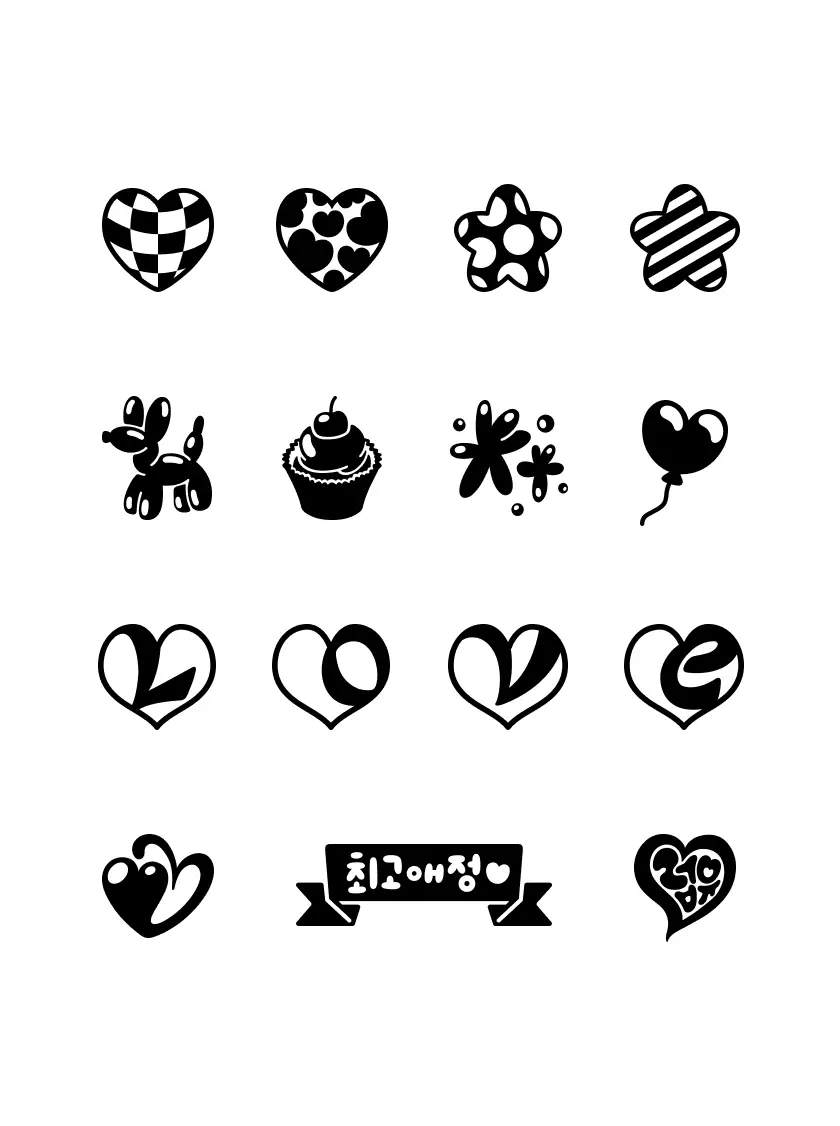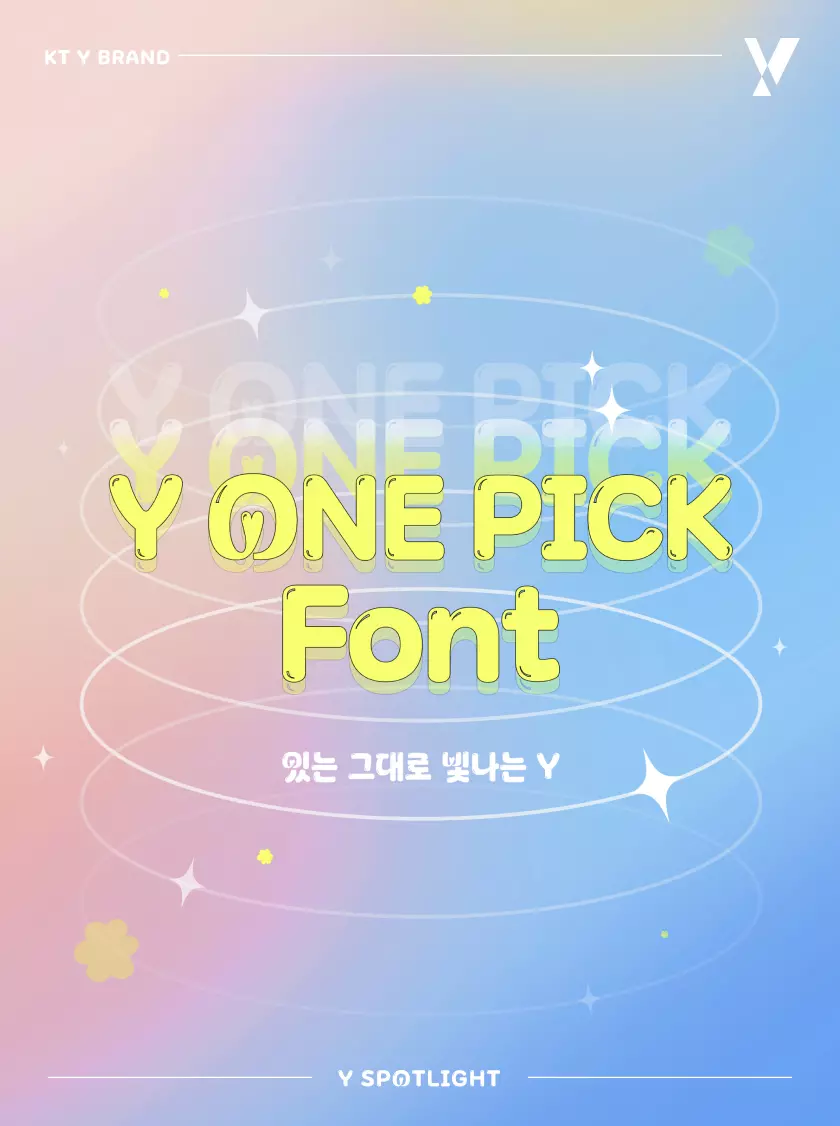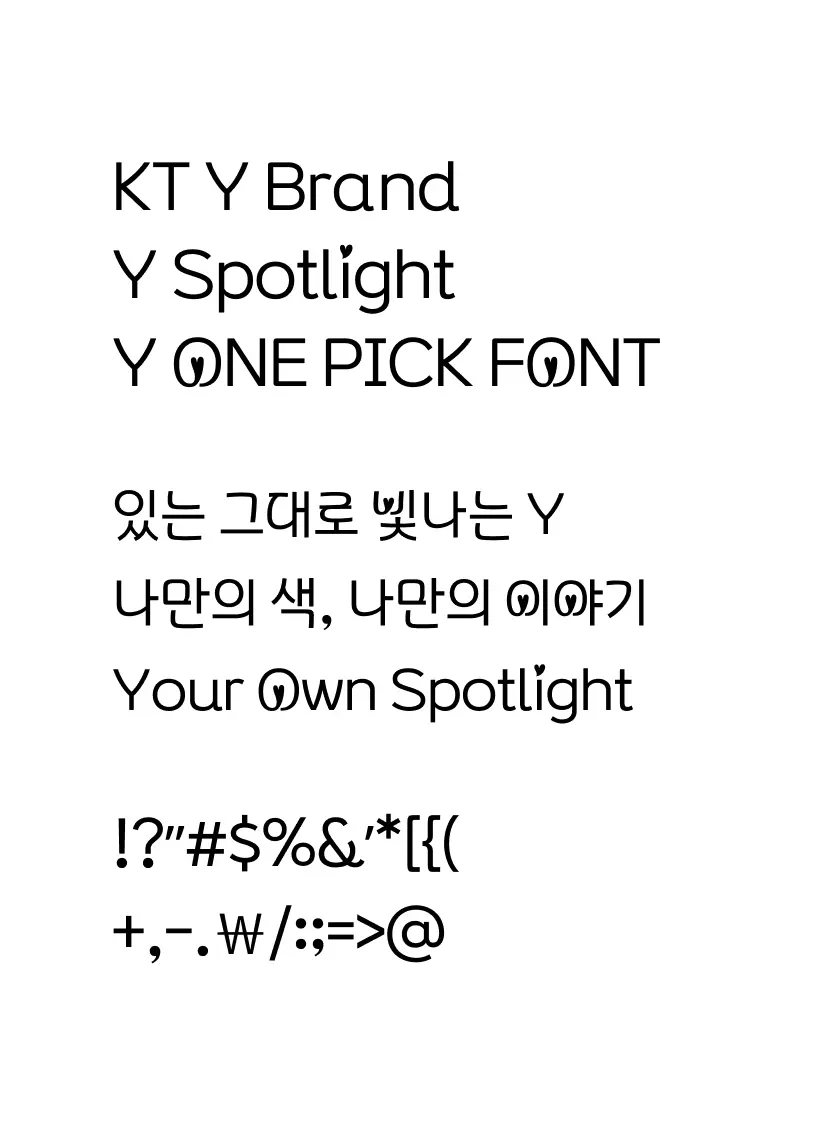
2024년 한글날을 맞이하여 무료 폰트로 배포한 KT Y최애체를 무료로 다운로드하는 방법을 살펴본다. 더불어 누구나 무료로 사용이 가능한 Y최애체를 컴퓨터에 설치하는 방법과 코딩 시에 사용하는 방법도 살펴본다.
누구나 개인적인 용도뿐만 아니라 상업적인 용도 즉, 영리 또는 비영리 목적으로도 무료로 사용할 수 있도록 제공하는 무료 폰트인 Y최애체를 소개한다. 해당 Y최애체는 KT 공식 대학생 마케팅 서포터즈인 Y퓨처리스트와 함께 MZ세대의 아이디어를 담아 제작된 글꼴로 팬덤 문화를 상징하는 하트와 풍선을 모티브로 하고 있다. 다음에서 Y최애체를 무료로 다운로드해서 컴퓨터에 설치하는 방법을 비롯해서 다양한 용도로 사용하는 자세한 방법을 확인할 수 있다.
KT에서 20대를 타깃으로 만든 브랜드인 Y를 담고 있는 KT Y 공식홈페이지에서 2024년에 한글날을 기념하여 제작한 브랜드 Y 전용서체인 Y최애체를 누구나 사용 가능한 무료 폰트로 배포하고 있다.
Y최애체는 아래의 이미지에서 보듯이 전체적으로 자유로운 곡선을 활용하면서 일부 자소에 하트가 담겨 있는데, 앞에서 언급했듯이 젊은 세대들의 팬덤 문화를 상징하는 하트와 풍선을 모티브로 한 MZ세대 특히 Z세대 특성을 반영한 글꼴이다.
더불어 컴퓨터 및 모바일에서 사용이 가능한 하트 모양 아이콘도 제공하는데, PC에서는 볼드체로 아이콘 입력이 가능하다. 단, 모바일에서는 별도 앱을 활용해서 폰트를 설치한 이후에 레귤러체로 아이콘을 입력할 수 있다.